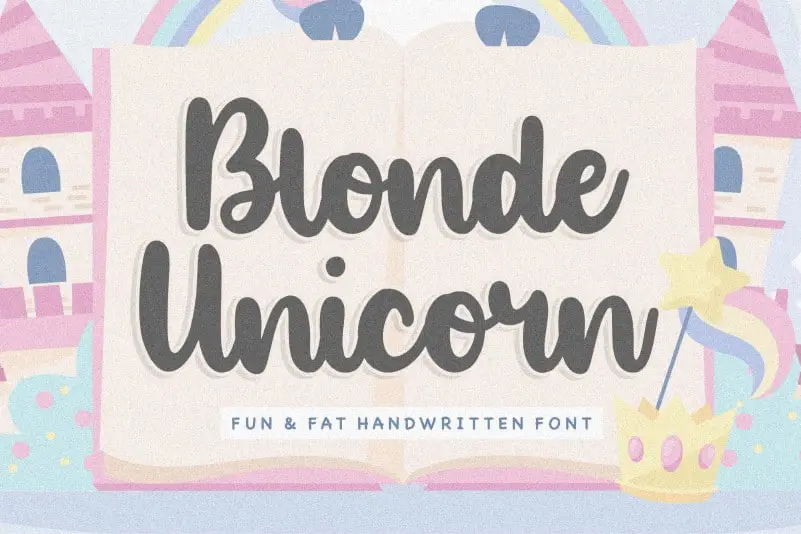
Blonde Unicorn Handwritten Font – Fonte Grátis
Blonde Unicorn Handwritten Font
A “Blonde Unicorn Handwritten Font” é uma delícia para quem busca um toque delicado e único em suas criações digitais. Com traços suaves e uma personalidade encantadora, essa fonte se encaixa perfeitamente em projetos como embalagens de produtos, identidades corporativas, magazines, redes sociais, até mesmo decoração para casamentos ou qualquer texto que você queira destacar sobre um fundo. Suave, feminina e cheia de encanto, a Blonde Unicorn Handwritten Font será uma ótima escolha para quem busca dar uma sensação a mais de personalidade aos seus materiais digitais. Não há dúvida de que ela irá fazer seu design brilhar ainda mais.